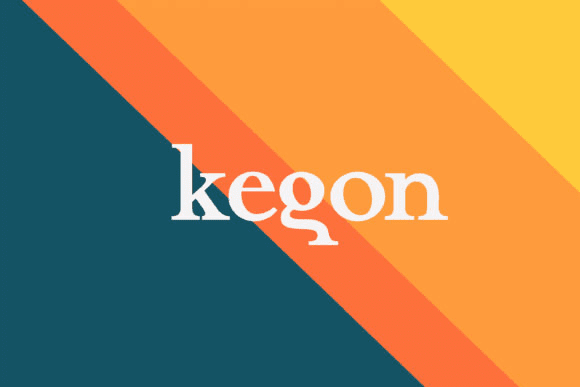
[Creativefabrica] Kegon Font (2021)
Название: Kegon Font (2021)
[Creativefabrica] Kegon Font (2021)
Kegon
- это классный, аутентичный и современный шрифт с засечками.
Этот шрифт идеально подходит для написания веб-дизайнов, визитных карточек и практически всего, что требует уникального штриха.